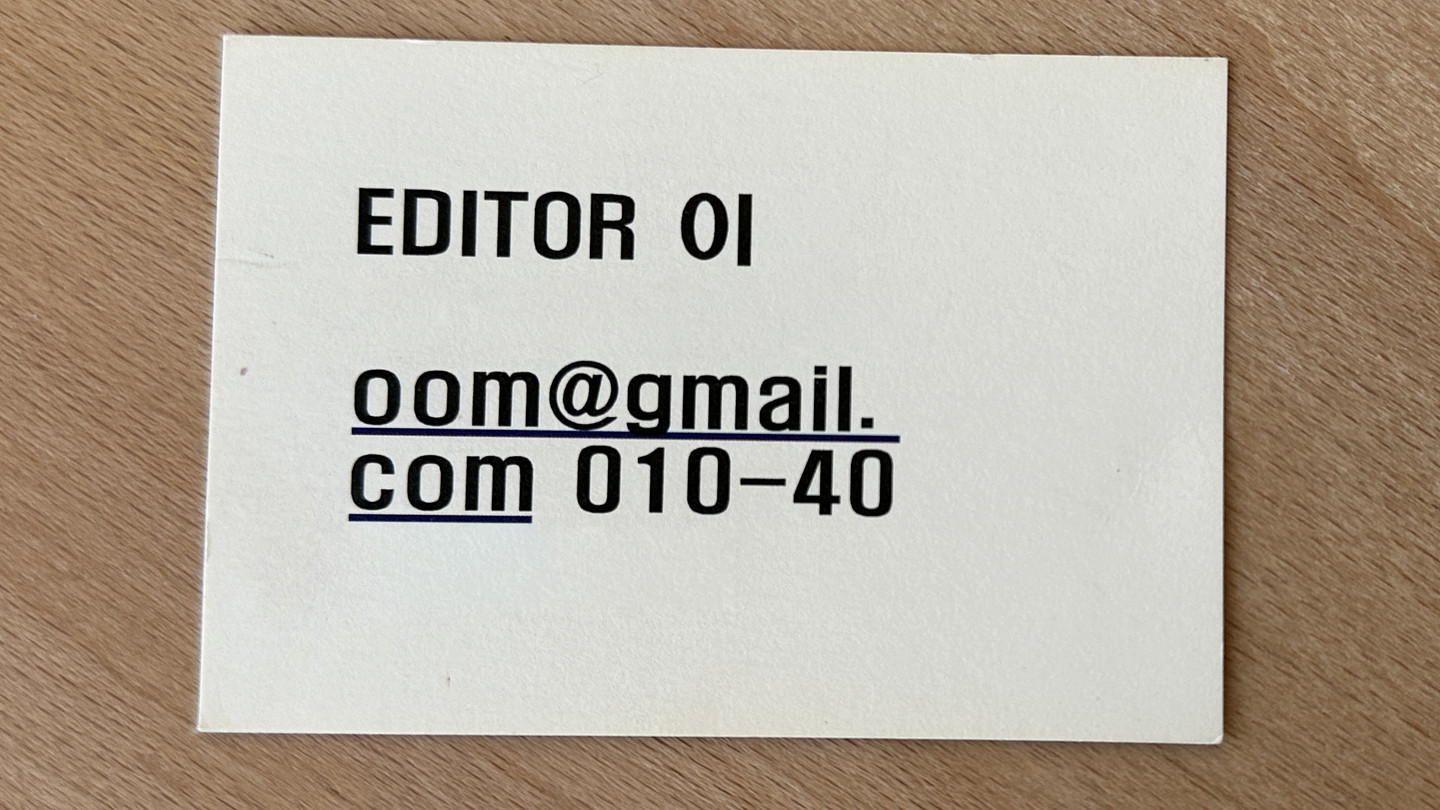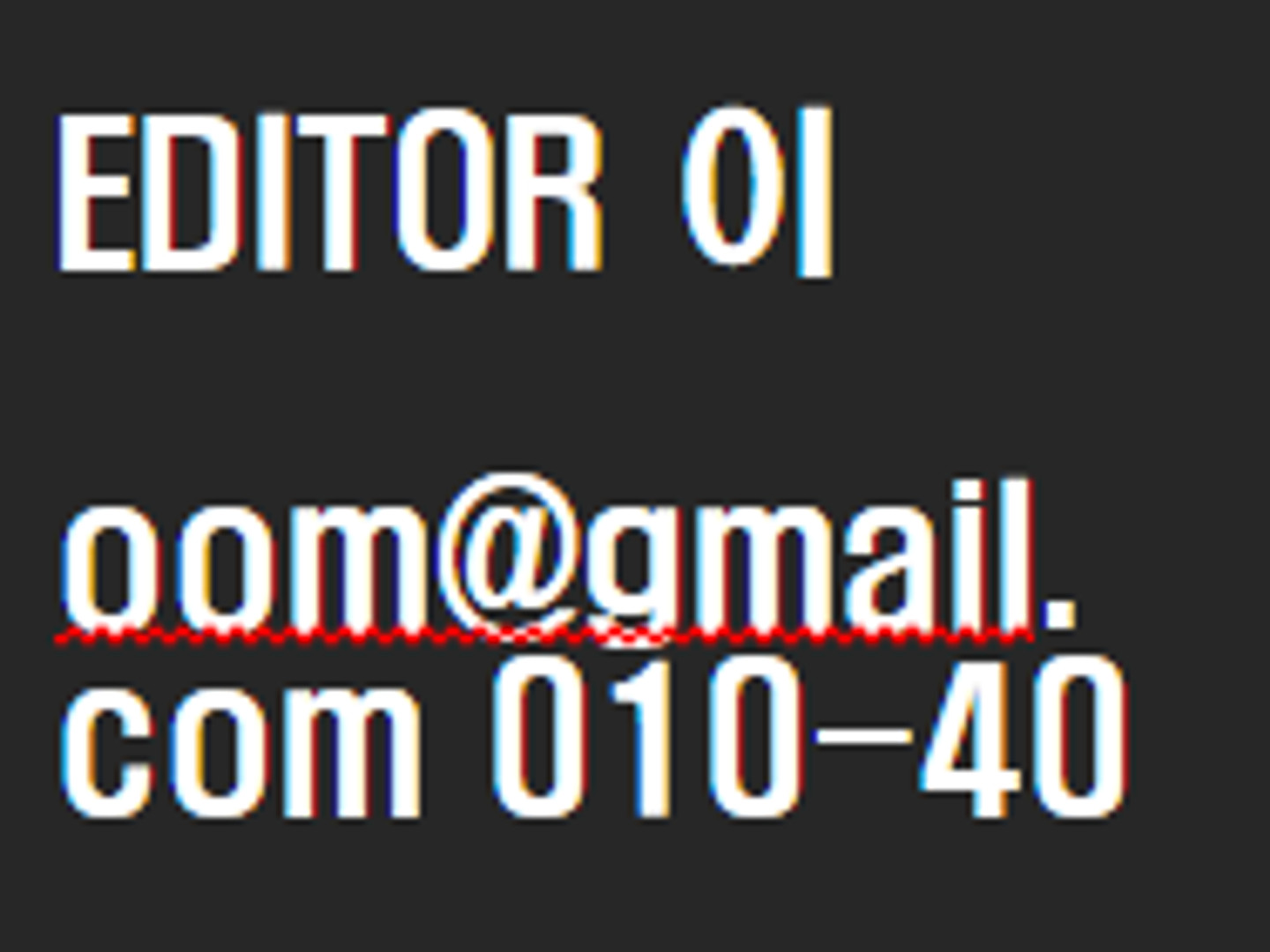
이전 작업자가 기본 폰트를 옆으로 늘려서 작업 하였다고 하는데 도통 찾을래 찾을수가 없네요.. 무슨 폰트인지 아시는분 계시면 알려주심 감사하겠습니다.
HY헤드라인
한글 프로그램에 기본적으로 포함되는 "HY헤드라인" 폰트네요. 참고로 이 폰트는 라이센스를 따로 구매하지 않으면 한컴오피스 프로그램 이외엔 사용이 불가능합니다.